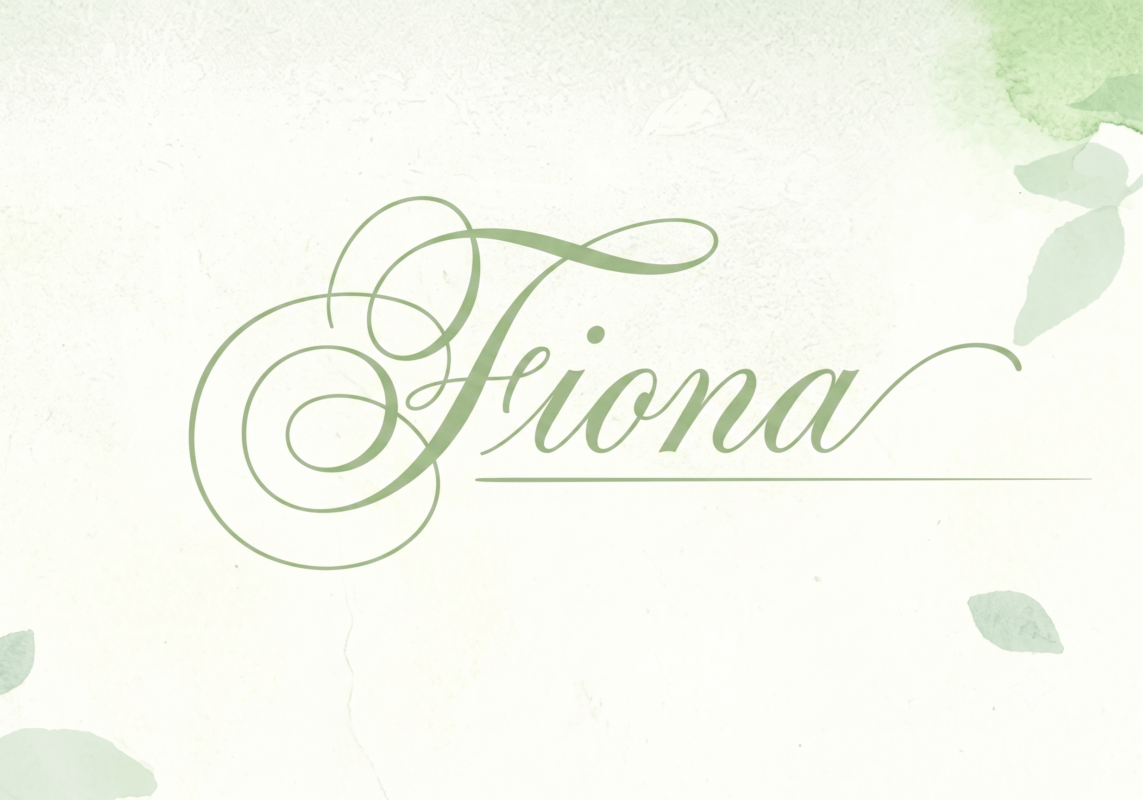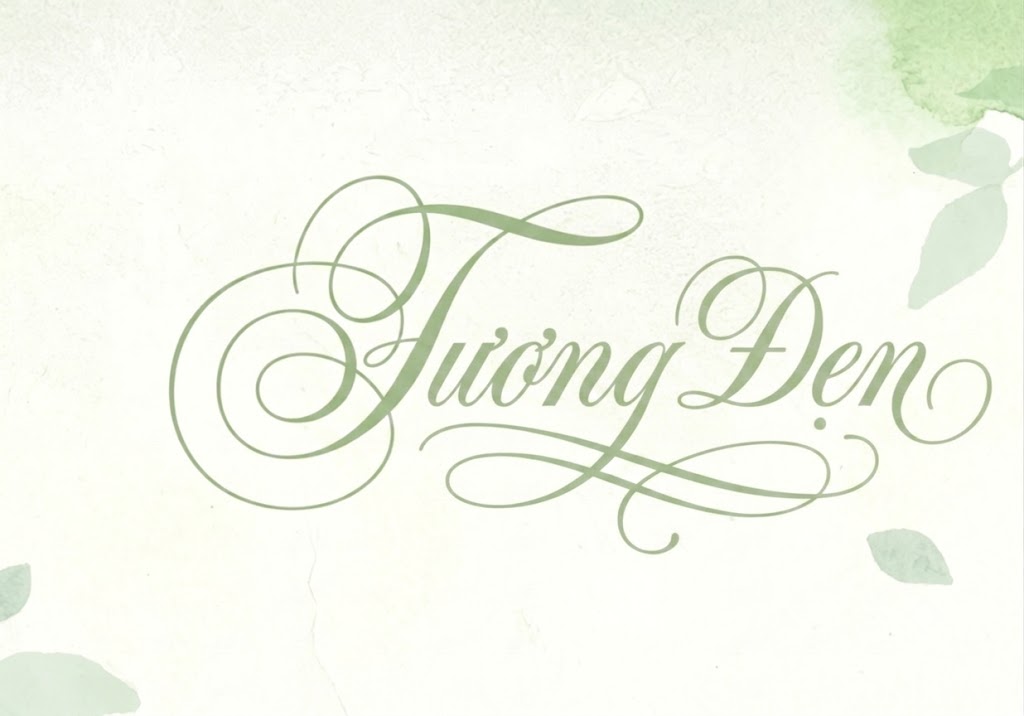
1FTV Magesta
Trong thiết kế đồ họa, font chữ không chỉ đóng vai trò truyền tải nội dung mà còn góp phần tạo nên cảm xúc, phong cách và dấu ấn riêng cho từng sản phẩm. Một font chữ phù hợp có thể giúp logo trở nên cao cấp hơn, poster thu hút hơn và bộ nhận diện thương hiệu trở nên chuyên nghiệp hơn. Trong số những font Việt hóa được nhiều designer quan tâm, 1FTV Magesta là một lựa chọn nổi bật nhờ phong cách thanh lịch, hiện đại và dễ ứng dụng.
1FTV Magesta là font chữ mang hơi hướng sang trọng, phù hợp với các thiết kế cần sự tinh tế, mềm mại nhưng vẫn giữ được vẻ chuyên nghiệp. Font này thường được sử dụng trong thiết kế logo, thương hiệu cá nhân, mỹ phẩm, thời trang, thiệp cưới, tiêu đề poster, banner quảng cáo và các ấn phẩm truyền thông cao cấp.
Giới Thiệu Chung Về 1FTV Magesta
1FTV Magesta là phiên bản font Việt hóa được xử lý để hỗ trợ tốt hơn cho nội dung tiếng Việt. Với đặc điểm đường nét mềm mại, cân đối và có tính thẩm mỹ cao, font chữ này giúp thiết kế trở nên nổi bật mà không gây cảm giác rối mắt.
Điểm mạnh của 1FTV Magesta nằm ở khả năng tạo cảm giác sang trọng ngay từ cái nhìn đầu tiên. Font phù hợp với những thiết kế cần thể hiện sự tinh tế, nữ tính, cao cấp hoặc mang hơi hướng nghệ thuật.
Đặc Điểm Nổi Bật Của Font 1FTV Magesta
Font 1FTV Magesta sở hữu nhiều đặc điểm phù hợp với nhu cầu thiết kế hiện đại. Trước hết, font có đường nét uyển chuyển, tạo cảm giác nhẹ nhàng và thanh thoát. Các ký tự được thiết kế hài hòa, giúp tổng thể văn bản trông đẹp mắt hơn khi dùng làm tiêu đề hoặc điểm nhấn.
Bên cạnh đó, 1FTV Magesta có độ nhận diện tốt, không quá đơn giản nhưng cũng không quá cầu kỳ. Nhờ vậy, font có thể sử dụng linh hoạt trong nhiều phong cách thiết kế khác nhau, từ tối giản, sang trọng cho đến nghệ thuật và thời trang.
Một ưu điểm quan trọng khác là font đã được Việt hóa, hỗ trợ các dấu tiếng Việt như ă, â, ê, ô, ơ, ư, đ. Điều này giúp người dùng hạn chế tình trạng lỗi dấu, lệch dấu hoặc mất ký tự khi thiết kế nội dung tiếng Việt.
Ứng Dụng Của 1FTV Magesta Trong Thiết Kế
1FTV Magesta có thể ứng dụng trong nhiều dạng thiết kế khác nhau. Với phong cách sang trọng và mềm mại, font này đặc biệt phù hợp cho các lĩnh vực cần sự tinh tế trong hình ảnh thương hiệu.
Bạn có thể sử dụng 1FTV Magesta để thiết kế logo cho thương hiệu thời trang, spa, mỹ phẩm, studio ảnh, tiệm hoa, tiệm bánh hoặc thương hiệu cá nhân. Khi đặt trong bố cục phù hợp, font giúp logo trở nên có chiều sâu và tạo cảm giác cao cấp hơn.
Ngoài ra, font cũng rất phù hợp để làm tiêu đề cho poster, banner, thiệp mời, thiệp cưới, menu nhà hàng, bài đăng mạng xã hội hoặc ảnh quote truyền cảm hứng. Với những thiết kế cần tạo điểm nhấn bằng chữ, 1FTV Magesta là một lựa chọn đáng cân nhắc.
Chi Tiết Bản Việt Hóa 1FTV Magesta
Điểm đáng chú ý của 1FTV Magesta là khả năng hỗ trợ tiếng Việt tốt hơn so với nhiều font gốc chưa được Việt hóa. Việc Việt hóa không chỉ đơn giản là thêm dấu mà còn cần căn chỉnh vị trí dấu, khoảng cách chữ và độ cân đối giữa các ký tự.
Nhờ được xử lý lại cho phù hợp với tiếng Việt, 1FTV Magesta giúp văn bản hiển thị tự nhiên hơn khi dùng trong thiết kế. Điều này đặc biệt quan trọng với các sản phẩm truyền thông tại Việt Nam, nơi font chữ cần vừa đẹp vừa đảm bảo khả năng đọc.
Vì Sao Nên Sử Dụng Font 1FTV Magesta?
Lý do đầu tiên khiến 1FTV Magesta được yêu thích là tính thẩm mỹ cao. Font mang lại cảm giác sang trọng, thanh lịch và chuyên nghiệp, rất phù hợp với những thiết kế cần tạo ấn tượng ngay từ phần nhìn.
Lý do thứ hai là khả năng ứng dụng linh hoạt. Dù bạn đang thiết kế logo, poster, thiệp cưới, banner quảng cáo hay bài đăng mạng xã hội, font này vẫn có thể phát huy hiệu quả nếu được phối hợp đúng bố cục và màu sắc.
Lý do thứ ba là font đã hỗ trợ tiếng Việt, giúp tiết kiệm thời gian chỉnh sửa khi thiết kế. Thay vì phải xử lý lỗi dấu hoặc thay font khác, bạn có thể sử dụng 1FTV Magesta trực tiếp cho các nội dung tiếng Việt.
Gợi Ý Cách Sử Dụng 1FTV Magesta Hiệu Quả
Để sử dụng 1FTV Magesta đẹp hơn, bạn nên dùng font này cho tiêu đề, logo hoặc các dòng chữ cần tạo điểm nhấn. Không nên dùng font cho đoạn văn bản quá dài vì phong cách chữ nghệ thuật thường phù hợp hơn với phần nổi bật.
Khi thiết kế, bạn có thể kết hợp 1FTV Magesta với các font sans-serif đơn giản để tạo sự cân bằng. Ví dụ, phần tiêu đề dùng Magesta để tạo cảm giác sang trọng, còn phần mô tả dùng font dễ đọc để đảm bảo người xem tiếp nhận thông tin rõ ràng.
Ngoài ra, font sẽ phát huy tốt hơn khi kết hợp với các tone màu như trắng, đen, vàng gold, be, nâu nhạt, hồng pastel hoặc xanh cổ điển. Đây là những màu thường phù hợp với phong cách cao cấp, nhẹ nhàng và tinh tế.
Nếu bạn đang tìm một font chữ vừa đẹp mắt, vừa dễ ứng dụng trong thiết kế logo, poster, thiệp mời, banner hoặc bài đăng mạng xã hội, 1FTV Magesta là một font đáng để trải nghiệm.